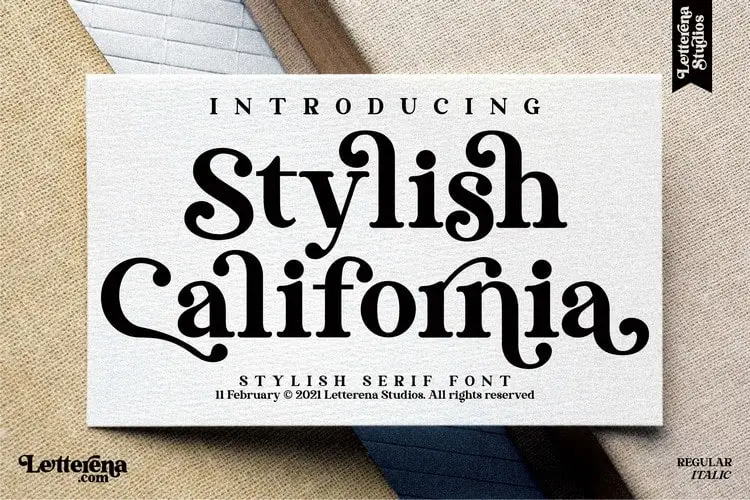
Stylish California Serif Font – Fonte Grátis
Stylish California Serif Font
A fonte “Stylish California Serif Font” é um design elegante que traz o melhor das serifas modernas com o charme vintage dos serifos tradicionais. Especificamente criada por Letterena Studios, esta tipografia séria se destaca entre as sans serif, oferecendo uma textura única e sofisticada para seus projetos. Perfeita tanto para ambientes corporativos quanto de design pessoal, a “Stylish California Serif Font” é uma escolha ideal para quem busca um toque refinado em sua identidade visual. Seja no formato de logotipos, embalagens ou até mesmo nos mais delicados materiais de decoração como cartões de convite e capas de livros, esta fonte traz a elegância que você precisa. Suave mas atemporal, ela é uma opção ideal para quem procura ar monótono, porém sofisticado. Sua versatilidade faz dela um recurso indispensável para qualquer projeto em busca de beleza e classe. Seja qual seja o seu campo, “Stylish California Serif Font” está aqui para transformar a aparência de seus trabalhos de design.